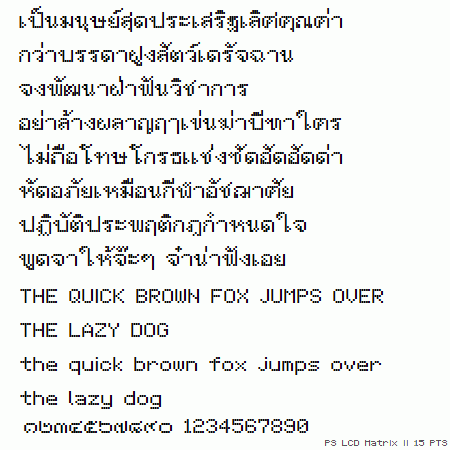
เป็นฟอนต์ที่เอาไว้ใช้งานออฟฟิศอย่างเดียว ดูบนจออาจจะไม่สวยเท่าไร แนะนำว่า ควรใช้ขนาด 7.5, 15, 30, 60 จึงจะดูดีบนหน้าจอ ส่วนบนเครื่องพิมพ์ขนาดเท่าไรก็ได้ครับ ออกได้หมด ฟอนต์นี้ได้แรงบรรดาลใจมาจากฟอนต์ของโนเกีย 3315 ไม่ต้องแปลกใจว่ามันช่างคล้ายกันเหลือเกิน
PS LCD Matrix II